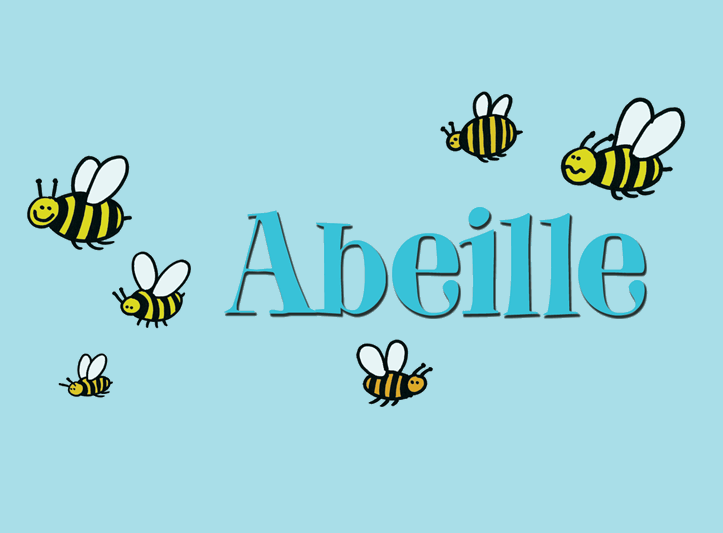
A Abeille é uma fonte serif elaborada por Hamilton que oferece um charme elegante e sofisticado para projetos digitais. Seu design suave, combinando linhas afiadas com textura delicada, cria um equilíbrio entre a simplicidade e o luxo. É perfeita para aplicativos de negócios ou editoriais que buscam um toque único e profissional. Este modelo demo é gratuito para uso pessoal, mas caso você deseje usá-la em aplicações comerciais, como jogos, apps ou software, deve comprar a versão completa que inclui ajustes de espaço inter-fonte, direitos de embedding, todos os caracteres (incluindo o 4) e extras disponíveis no meu site: hanodedfonts.com. Para adquirir um licenciamento para uso em jogos, apps ou software, visite www.hanodedfonts.com ou leia o arquivo FAQ incluído na pasta zip. A fonte Abeille é uma escolha incrível para qualquer projeto que busque elegância e sofisticação.